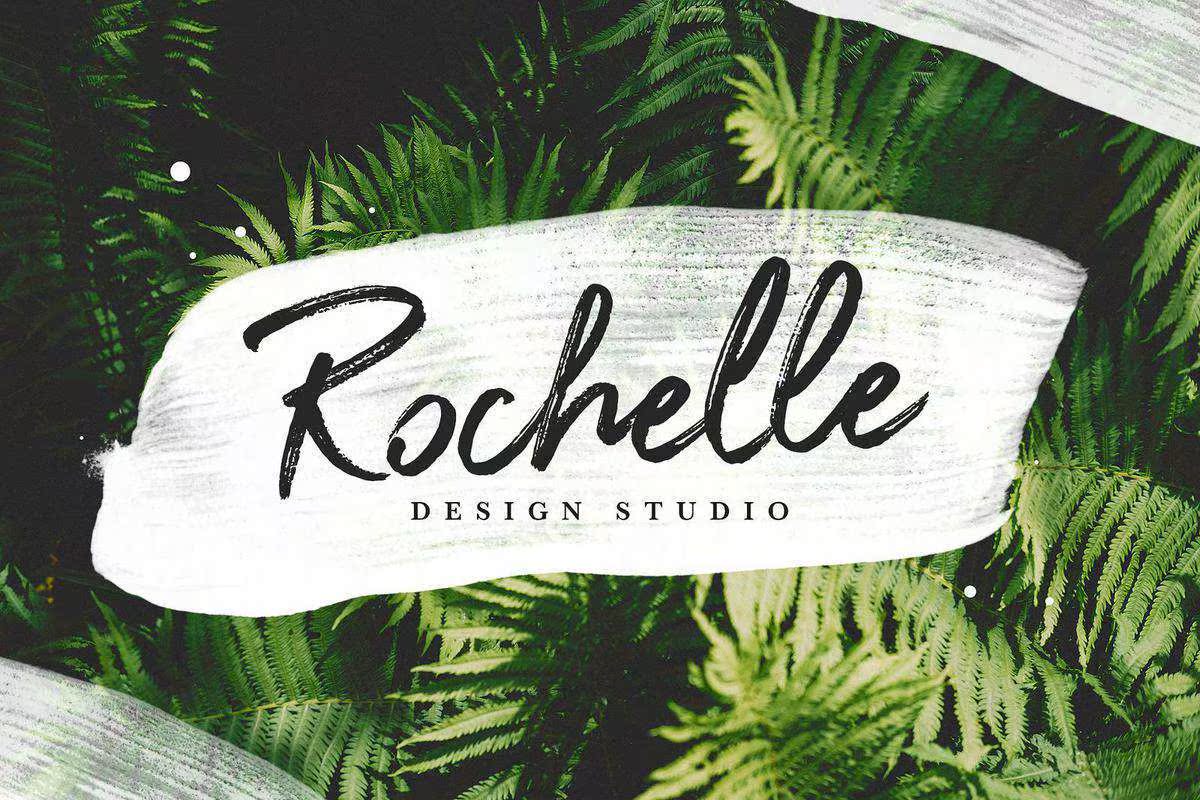
简介Perfetto–A并使用AuthenticDryBrushStrokesDrawNonPer书写BrushFonto。完美的徽标设计、posterdesign、社交媒体、印刷报价、封面照片、封面和包装设计。简介Perfetto–A并使用AuthenticDryBrushStrokesDrawNonPer书写BrushFonto。完美的徽标设计、posterdesign、社交媒体,印刷报价包括照片、封面和包装设计。